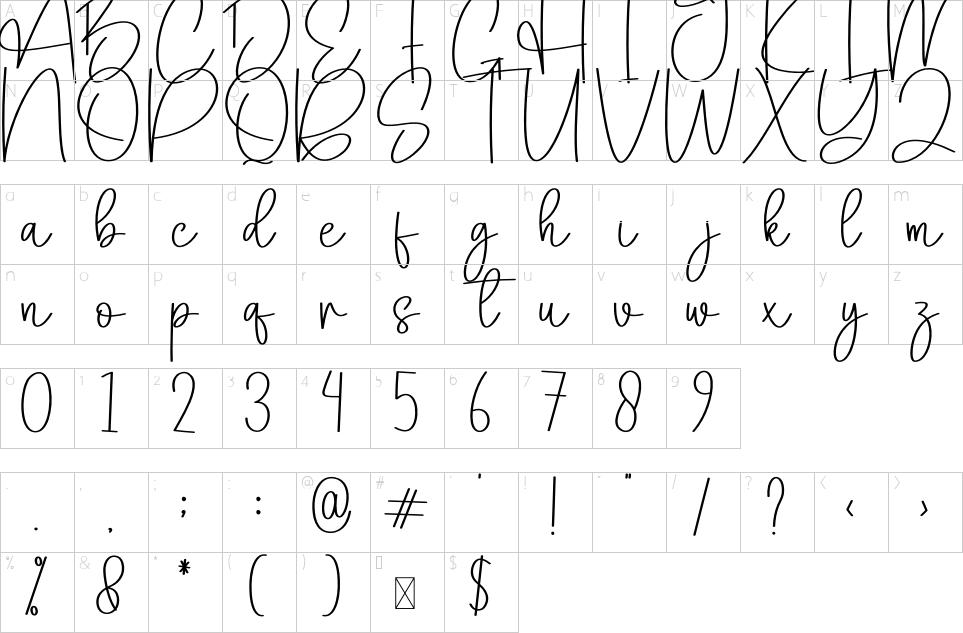
A fonte Saturday é uma opção de fonte grátis para designers e criativos que estão buscando uma escolha natural e envolvente. Desenhada por scratchones, esta fonte oferece uma mistura harmônica de linhas suaves e traços bem definidos. Ela foi projetada para se encaixar perfeitamente em várias aplicações, desde textos digitais até design de editoração de fotos. Com um total de 290 downloads, Saturday é uma opção popular para aqueles buscando uma fonte versátil e moderna. Sem dúvida, ela será um adorno visual atraente para qualquer projeto. Se você está procurando por uma fonte elegante e acessível, Saturday pode ser uma escolha perfeita. Download hoje para experimentar a versatilidade desta fonte.